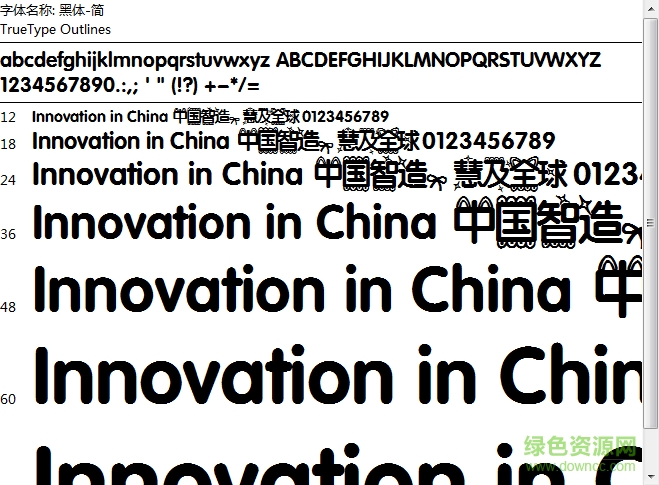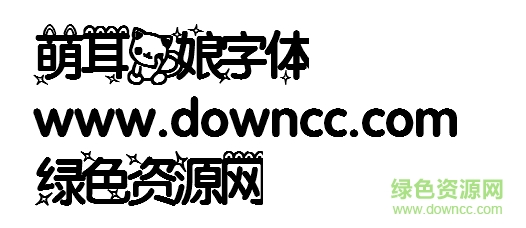
萌耳貓娘字體是貓叔創(chuàng)作的一款非常Q萌可愛(ài)的藝術(shù)字體,在每個(gè)中文字上都加上了可愛(ài)的貓耳、貓爪或星星圖案,讓它們活潑生動(dòng)起來(lái),喜歡的朋友就快來(lái)綠色資源網(wǎng)下載吧!
萌耳貓娘,它能夠?yàn)槲淖衷黾用让鹊呢埗洹⒑Y(jié)等素材,讓字體看起來(lái)更加“淑弱萌”,是一款可愛(ài)的卡通字體!